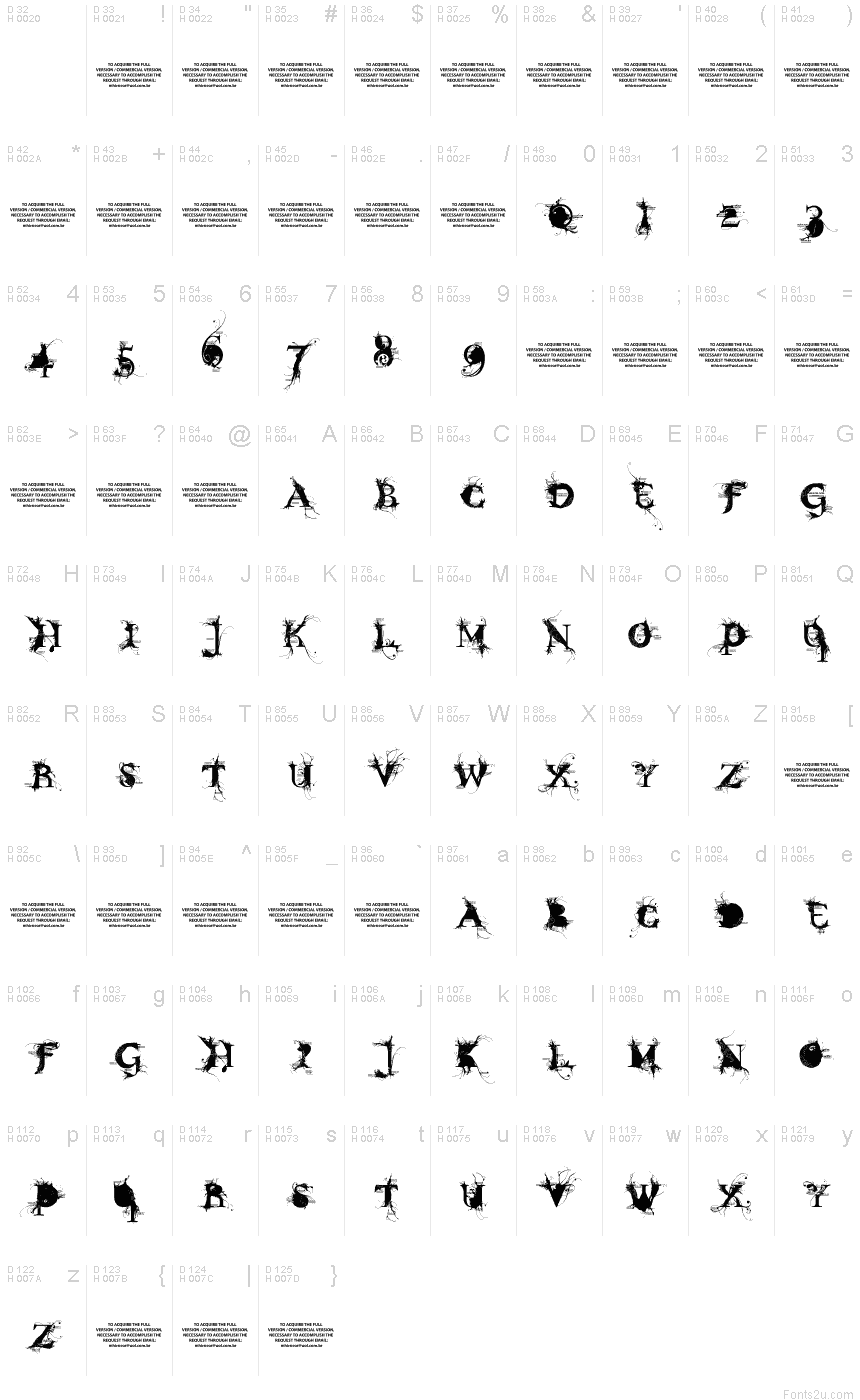
Bondage, který v roce 2007 vytvořil Marcio Hirosse, je bezplatné, děsivé dekorativní písmo s gotickým a nespoutaným charakterem. Písmena působí jako vytesaná z těžkých, starých forem, které pohltily trnité kořeny a popínavé výhonky. Kombinace ostré patkové struktury, rozpitého okraje a drátěných botanických detailů dodává textu dojem, jako by byl napůl živý.
Hodí se na hororové plakáty, metalové letáky, temné knižní obálky, halloweenskou grafiku i titulky, kde toto bezplatné písmo dokáže okamžitě navodit divokou a zlověstnou atmosféru. Využijte ho pro krátké nadpisy, názvy kapel, loga nebo iniciály, zejména pokud chcete, aby samotná typografie díky svým propleteným a plazivým prvkům určila náladu celého vizuálu.